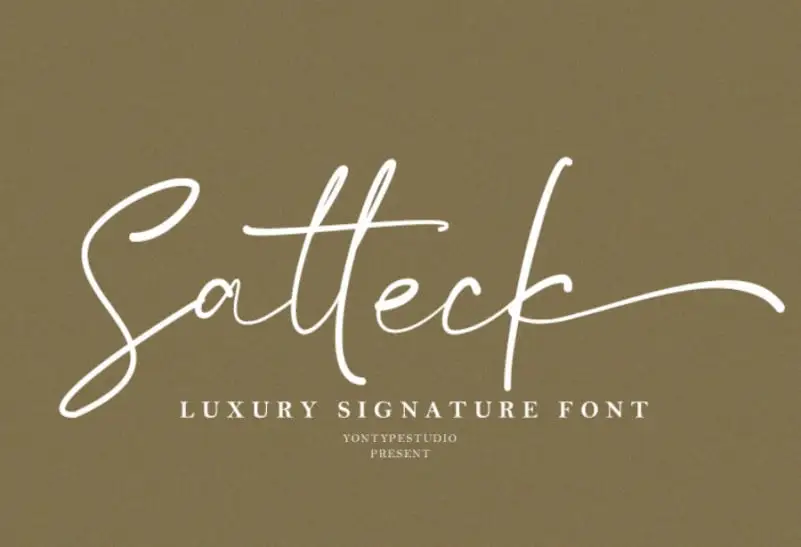
Satteck A Luxury Calligraphy Font – Download Grátis
A Satteck A Luxury Calligraphy Font é uma elegante tipografia script que se destaca por sua sofisticação e delicadeza. Perfeita para qualquer projeto requintado, esta fonte traz à vida as mais refinadas criações de design, especialmente indicada para cartões de convidados, cartões de agradecimento, citações, cartazes de aniversário, logotipos e cartões de negócios. Suas linhas finas e detalhes cuidadosamente projetados dão vida à sua escrita personalizada e tornam seus trabalhos ainda mais únicos e memoráveis. Com Satteck A Luxury Calligraphy Font na sua carteira de ferramentas, você sempre terá a opção perfeita para aquele projeto que exige um toque autêntico e elegante.
Designer: yontype